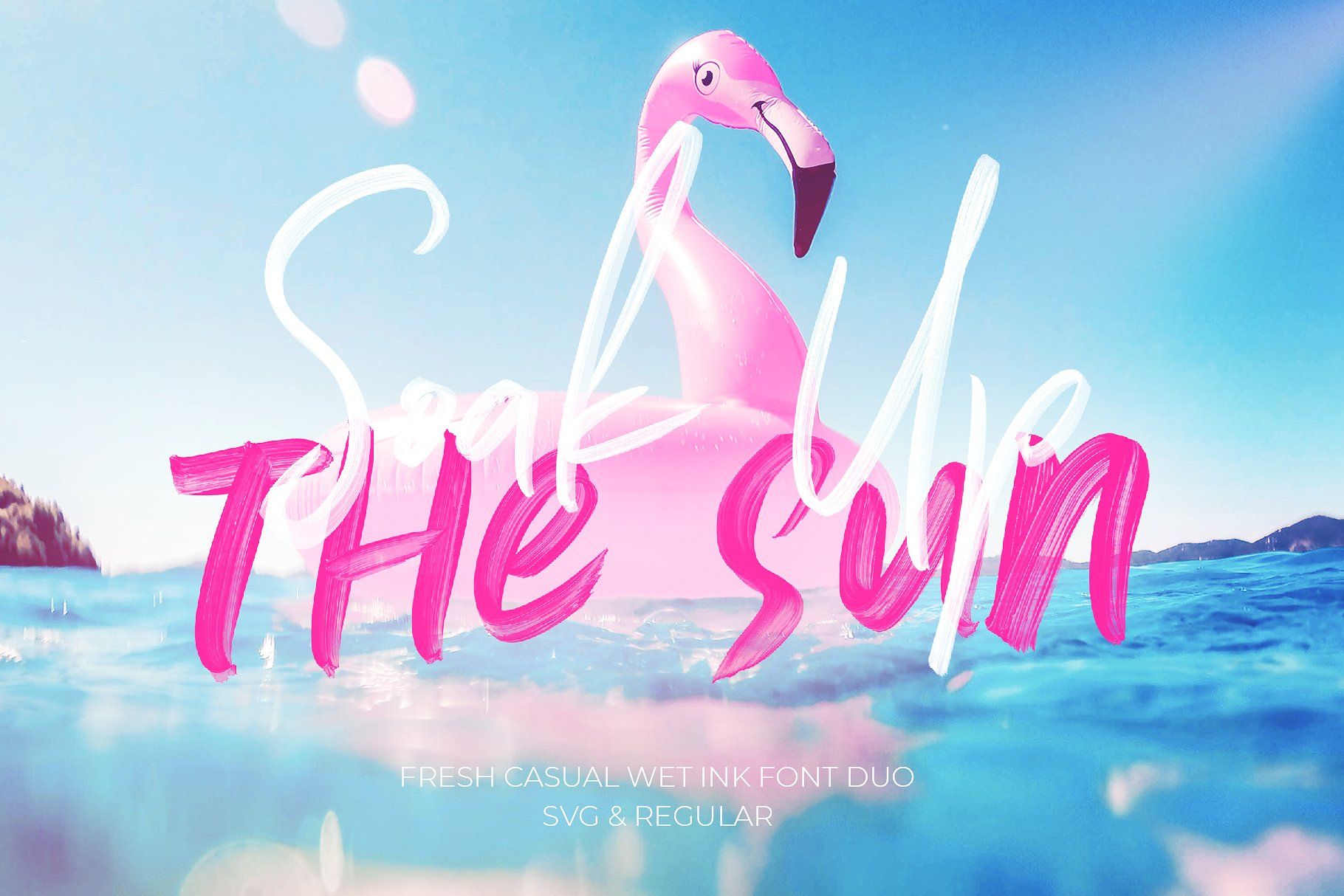
Soak Up The Sun Font Duo + SVG
Погрузитесь на пляж этим летом с помощью нашей новой коллекции Soak Up The Sun Font.
Представление текстурированных рукописных шрифтов SVG с эффектами влажных чернил.
Почувствуйте ручную любовь к этому продукту. Мы создали его вручную, превратив его в цифровой с высоким разрешением.
Этот дуэт шрифта представляет собой комбинацию подписи и смелых стилей.